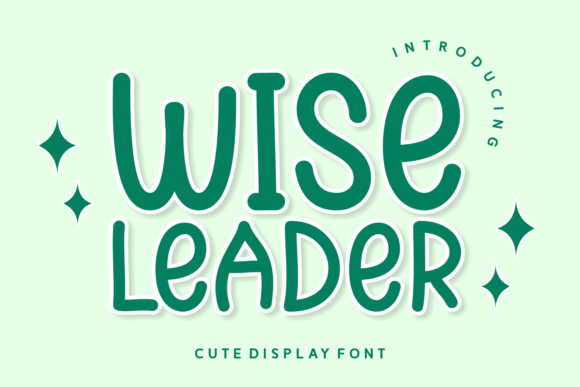
Wise Leader
適切なデザイン要素を見つけるのは難しい場合がありますが、Wise Leaderは作品を即座に引き立てる優れたコレクションを提供します。
POD(オンデマンド印刷)製品、結婚式の招待状、またはソーシャルメディアのグラフィックを作成している場合でも、Wise Leaderは理想的です。